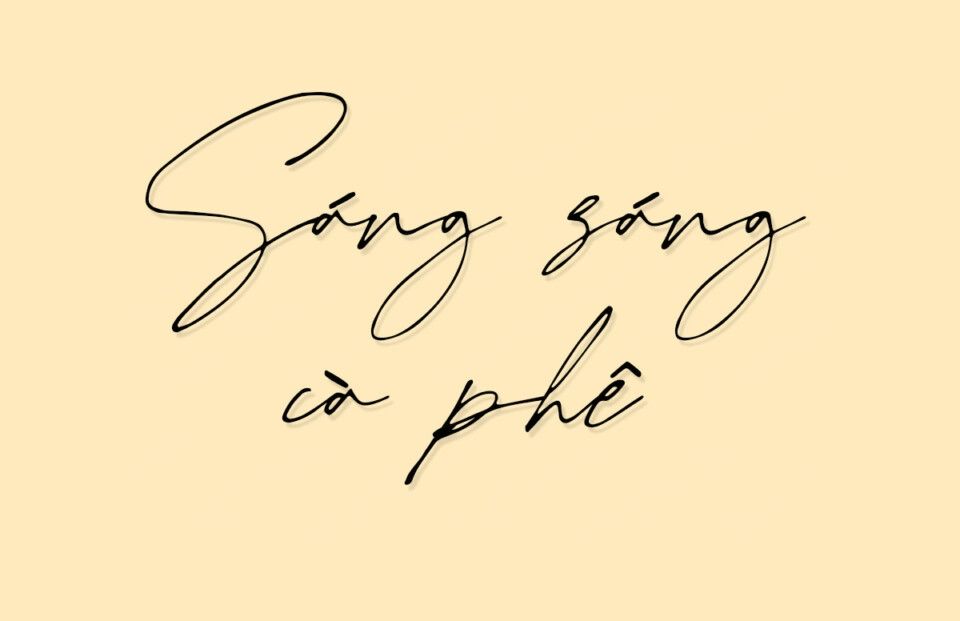
Nếu bạn đang tìm kiếm một làn gió mới cho các thiết kế đồ họa của mình, Font Việt hóa 1FTV VIP Saktere Handdrawn chính là sự lựa chọn hoàn hảo không thể bỏ qua. Với đường nét viết tay phóng khoáng, tự nhiên nhưng không kém phần tinh tế, bộ font này mang lại cảm giác gần gũi và đầy tính nghệ thuật cho từng tác phẩm. Được việt hóa chỉn chu đến từng dấu thanh, 1FTV VIP Saktere Handdrawn hứa hẹn sẽ giải phóng tiềm năng sáng tạo của bạn trong mọi dự án thiết kế.
Font Việt Hóa 1FTV VIP Saktere Handdrawn – Lựa Chọn Typography Viết Tay Đỉnh Cao Cho Designer
Trong thế giới thiết kế đồ họa hiện đại, việc lựa chọn font chữ phù hợp đóng vai trò quyết định đến 80% sự thành công của một sản phẩm truyền thông thị giác. Font Việt hóa 1FTV VIP Saktere Handdrawn ra đời nhằm đáp ứng nhu cầu ngày càng cao về một bộ font viết tay vừa mang tính cá bản, vừa đảm bảo tính ứng dụng thực tế. Sự kết hợp giữa phong cách nét vẽ thủ công (handdrawn) mộc mạc và chuẩn mực typography chuẩn tiếng Việt giúp bộ font này dễ dàng chinh phục cả những nhà thiết kế khó tính nhất.
Không giống như những font chữ công nghiệp cứng nhắc, Saktere Handdrawn đem đến cảm giác chân thật như được viết bằng bút mực trên chất liệu giấy cao cấp. Nhờ quy trình việt hóa công phu từ nhóm phát triển 1FTV VIP, các ký tự tiếng Việt với dấu câu phức tạp vẫn giữ nguyên được độ nảy, tính cân đối và sự mượt mà vốn có của bản gốc. Đây chắc chắn là công cụ đắc lực giúp nâng tầm các dự án nhận diện thương hiệu, thiết kế bao bì, banner quảng cáo hay nội dung mạng xã hội.
1. Phong Cách Handdrawn Mộc Mạc, Tự Nhiên Và Đậm Tính Nghệ Thuật
Điểm thu hút đầu tiên của Font Việt hóa 1FTV VIP Saktere Handdrawn chính là những đường nét mang đậm dấu ấn cá nhân và cảm xúc con người. Mỗi ký tự đều được tạo dựng với độ biến thiên nét đậm – nét mảnh ngẫu hứng, mô phỏng hoàn hảo thao tác đưa bút thủ công. Phong cách này giúp sản phẩm thiết kế thoát khỏi sự nhàm chán của các bộ font hệ thống, tạo ra chiều sâu thị giác và sự kết nối cảm xúc mạnh mẽ với người xem.
Nét chữ của Saktere Handdrawn vừa có độ rủ mềm mại của dòng chảy chữ viết tay, vừa có sự dứt khoát của những cú đi nét sáng tạo. Điều này làm cho font chữ trở nên cực kỳ nổi bật khi xuất hiện ở các vị trí quan trọng như tiêu đề chính, slogan hay các câu dẫn quan trọng trong bố cục.
2. Bộ Ký Tự Tiếng Việt Được Việt Hóa Chuẩn Tỉ Mỉ Và Cân Bằng Dấu Thanh
Một trong những thách thức lớn nhất khi sử dụng font chữ nước ngoài là hiện tượng lỗi font tiếng Việt hoặc dấu thanh bị lệch, mất thẩm mỹ. Với Font 1FTV VIP Saktere Handdrawn, vấn đề này đã được xử lý hoàn toàn triệt để. Hệ thống dấu câu như sắc, huyền, hỏi, ngã, nặng cùng các ký tự đặc trưng như ê, ơ, ư, đ đã được thiết kế lại hoàn toàn thủ công để phù hợp với độ nghiêng và cấu trúc của từng chữ cái gốc.
Sự tỉ mỉ này đảm bảo rằng khi bạn gõ văn bản tiếng Việt dài hay các cụm từ có nhiều dấu xếp đè lên nhau, bố cục chữ vẫn giữ được sự thông thoáng, không bị rối mắt hay dính nét. Độ kerning (khoảng cách giữa các chữ cái) cũng được tối ưu hóa nhằm tạo nên một dòng chảy văn bản tự nhiên và êm mắt nhất.
3. Tích Hợp Hệ Thống Alternates Và Ligatures Phong Phú
Để tăng tính biến hóa cho các tác phẩm typography, bộ font 1FTV VIP Saktere Handdrawn cung cấp hàng loạt các ký tự thay thế (Stylistic Alternates) và ký tự nối liền (Ligatures). Điều này cho phép nhà thiết kế tự do tùy biến các điểm đầu và điểm kết thúc của từ ngữ, tạo nên những tác phẩm chữ nghệ thuật mang dấu ấn riêng biệt mà không lo đụng hàng.
Nhờ tính năng này, bạn có thể dễ dàng biến tấu một từ đơn giản thành một cụm chữ nghệ thuật độc đáo chỉ với vài thao tác chọn ký tự thay thế trong các phần mềm đồ họa chuyên nghiệp. Đây là tính năng cao cấp thường chỉ xuất hiện trên các bộ font VIP chất lượng cao.
4. Khả Năng Ứng Dụng Đa Dạng Trong Nhiều Lĩnh Vực Thiết Kế
Font Việt hóa 1FTV VIP Saktere Handdrawn sở hữu tính đa dụng ấn tượng, có thể biến hóa linh hoạt để phù hợp với nhiều phong cách thiết kế khác nhau từ cổ điển (vintage/retro) đến hiện đại, tối giản:
- Thiết kế nhận diện thương hiệu: Thích hợp làm logo, nhãn mác cho các thương hiệu thời trang, tiệm bánh, quán coffee, sản phẩm handmade, spa & beauty.
- Ấn phẩm truyền thông & Quảng cáo: Tạo điểm nhấn thu hút trên poster, banner Facebook, Instagram Story, cover album hay thumbnail YouTube.
- In ấn & Bao bì: Xuất sắc khi ứng dụng trên bao bì sản phẩm, túi giấy, thiệp cưới, thiệp mời sự kiện, menu nhà hàng hay bìa sách.
- Trích dẫn nghệ thuật (Typography Quotes): Lý tưởng để sáng tạo các bức tranh trích dẫn truyền cảm hứng treo tường hoặc đăng tải trên mạng xã hội.
5. Tối Ưu Hóa Kỹ Thuật Tương Thích Mượt Mà Trên Mọi Phần Mềm